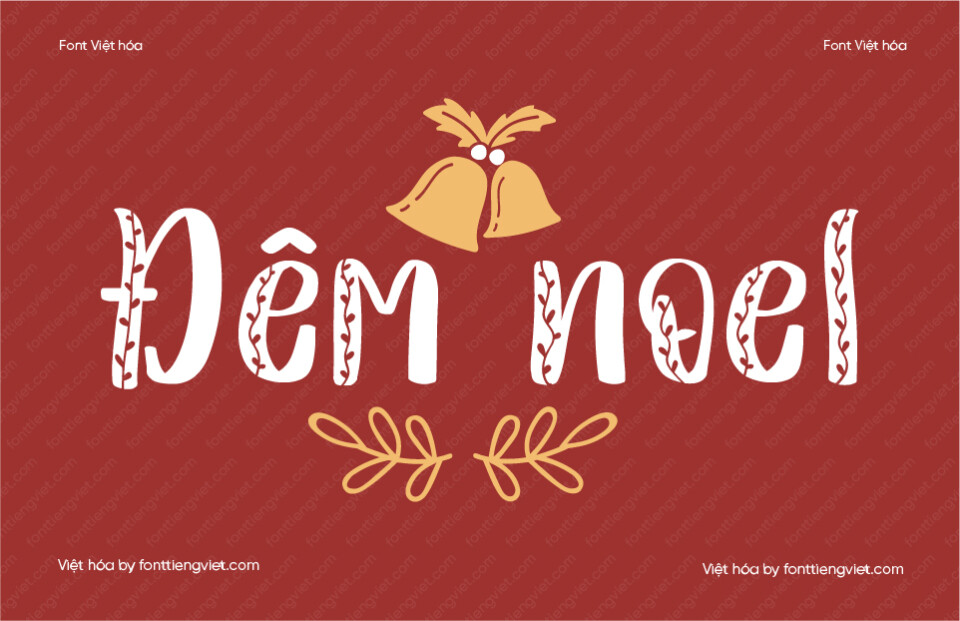
Font Việt hóa 1FTV VIP Christmas Leaf
Font Việt hóa 1FTV VIP Christmas Leaf – Font Noel trang trí nổi bật cho mùa lễ hội
Mùa Giáng Sinh luôn là thời điểm “vàng” để tạo ra những thiết kế ấn tượng như poster chương trình, banner khuyến mãi, thiệp chúc mừng hay hình ảnh truyền thông trên mạng xã hội. Để giúp bạn tiết kiệm thời gian mà vẫn có sản phẩm bắt mắt, Font Việt hóa 1FTV VIP Christmas Leaf là một gợi ý cực kỳ đáng thử. Đây là font chữ Noel mang phong cách trang trí với chi tiết mềm mại, gợi cảm giác ấm áp – vui tươi, và đặc biệt đã Việt hóa đầy đủ dấu để dùng ngay cho các thiết kế tiếng Việt.
1FTV VIP Christmas Leaf có gì nổi bật?
Điểm mạnh của Christmas Leaf nằm ở nét chữ trang trí độc đáo, phù hợp chủ đề lễ hội cuối năm. Font tạo cảm giác thân thiện, tươi sáng và dễ kết hợp với nhiều phong cách thiết kế: từ tối giản đến rực rỡ màu sắc. Khi bạn cần một font chữ mang “chất Noel” rõ ràng mà vẫn dễ đọc trên banner, poster hoặc ảnh bìa, đây là lựa chọn rất hợp lý.
Hỗ trợ tiếng Việt đầy đủ – thiết kế không còn lỗi dấu
Nhiều font Noel đẹp thường gặp vấn đề thiếu dấu tiếng Việt, dẫn đến phải chỉnh sửa thủ công hoặc thay thế ký tự. Với Font Việt hóa 1FTV VIP Christmas Leaf, bạn có thể gõ tiếng Việt bình thường, đảm bảo văn bản hiển thị chuẩn và đồng bộ, giúp tiết kiệm thời gian thiết kế đáng kể.
Ứng dụng thực tế của font Christmas Leaf Việt hóa
Bạn có thể dùng font này trong rất nhiều ấn phẩm mùa lễ hội:
• Poster chương trình Noel, Year End Party
• Banner khuyến mãi Giáng Sinh – Tết dương
• Thiệp chúc mừng, thiệp mời sự kiện
• Thiết kế social: cover Facebook, Instagram post, story
• Trang trí tiêu đề sản phẩm, nhãn quà tặng